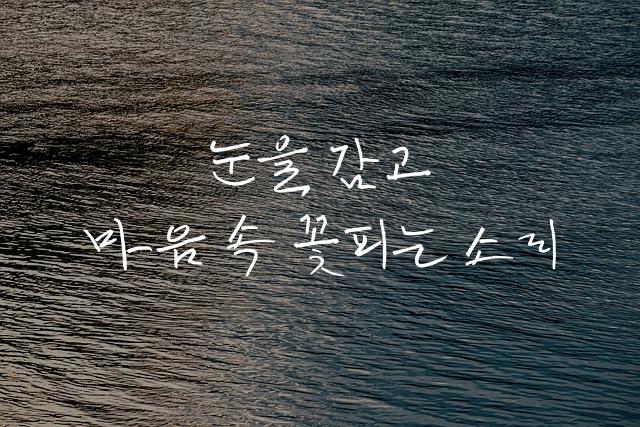
윤봉길체는 GS칼텍스에서 제작한 폰트로, 삐뚤빼뚤한 어른 손글씨의 감성을 담고 있습니다. 이 폰트는 따뜻하고 친근한 느낌을 전달하며, 독특한 개성을 강조합니다.
윤봉길체은(는)
손글씨, 감성적인, 부드러움 계열의 생김새를 가지고 있으며
출판 디자인, 출판물 제목 등에서 자주 활용되며, 효과적인 메시지 전달에 적합합니다.
이 폰트는 출판/미디어, 문화/예술 분야에 잘 어울리며,
신뢰감, 클래식한 느낌을 담고 있는 것이 특징입니다.